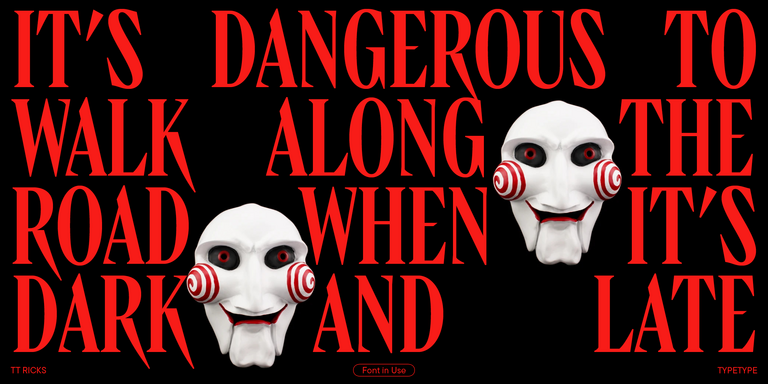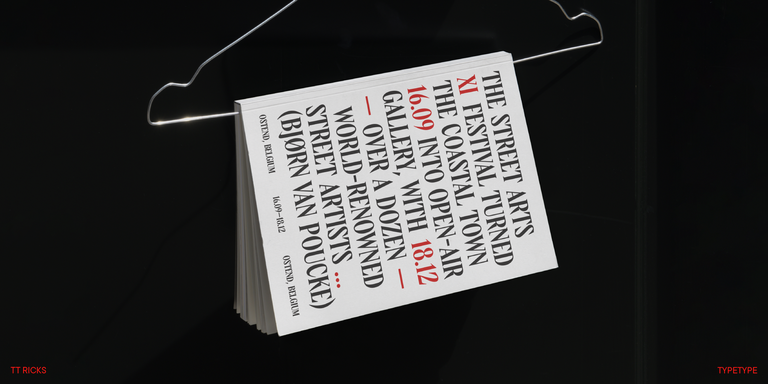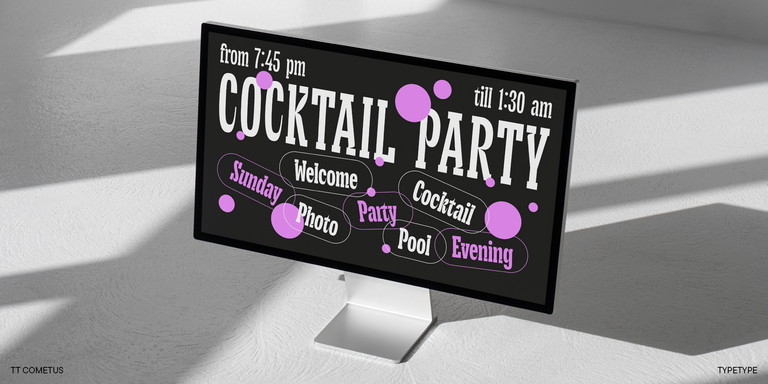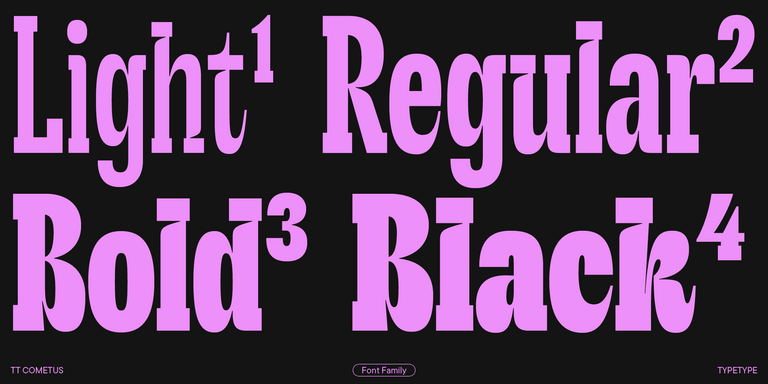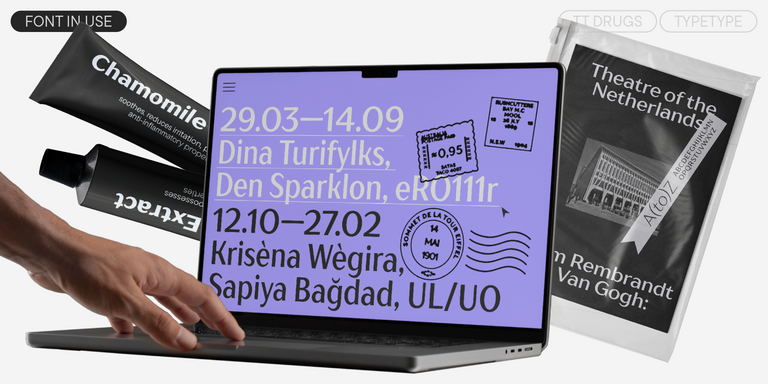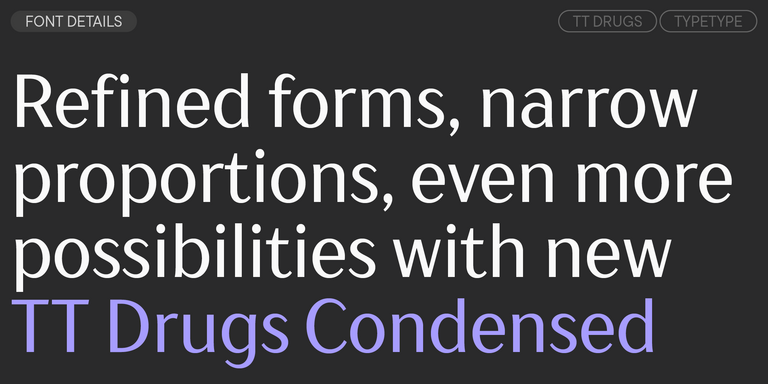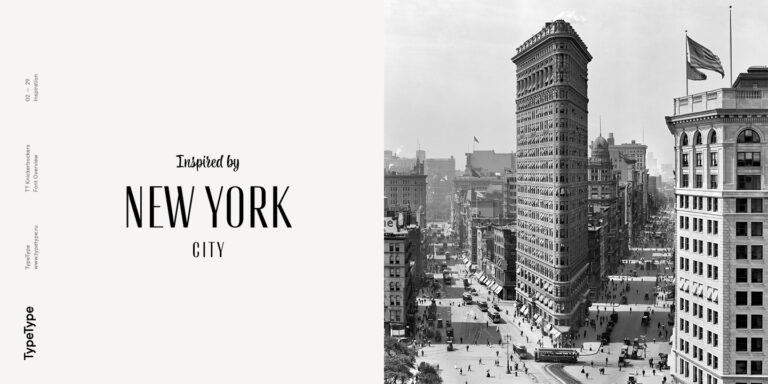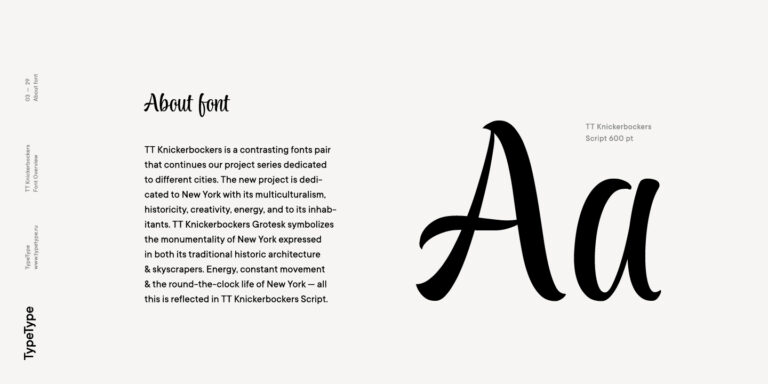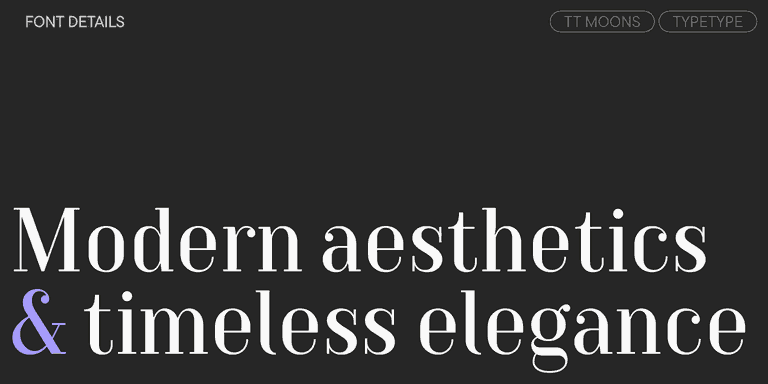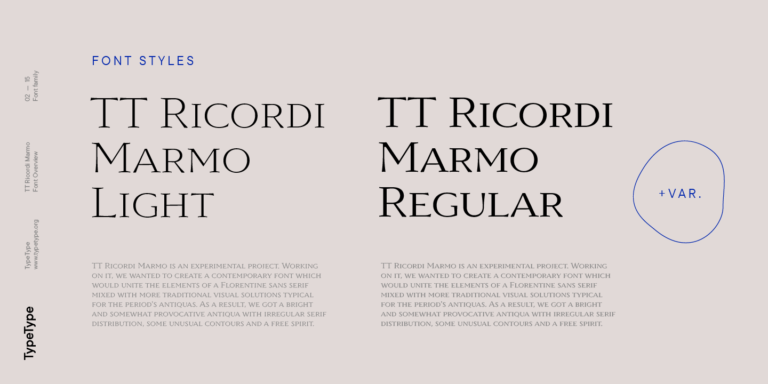
TT Moons est une serif fine et contrastée. Cette famille de caractères fonctionne particulièrement bien dans les designs classiques. TT Moons appartient au style des typographies modernes glyptales.
Polices similaires à Nimbus Roman No. 9 L
Si vous en avez assez des polices surutilisées et que vous recherchez des polices similaires à Nimbus Roman No. 9 L, découvrez nos meilleures alternatives à Nimbus Roman No. 9 L gratuites à essayer, qui présentent des caractéristiques proches ainsi que des éléments de design nouveaux et uniques. Certaines polices appartiennent à la même catégorie typographique, tandis que d’autres conviennent aux mêmes usages ou partagent des traits similaires, tout en se distinguant par leurs détails ou leurs proportions spécifiques.
Chez TypeType, vous trouverez des polices innovantes comme Nimbus Roman No. 9 L, et même mieux : voici une sélection d’alternatives à Nimbus Roman No. 9 L remarquables et moins répandues. Utilisez cette liste de polices de haute qualité similaires à Nimbus Roman No. 9 L selon vos besoins. Notre sélection offre un éventail plus large d’options pour choisir la meilleure police pour votre projet et renouveler vos designs. Toutes les polices présentées dans cette collection sont disponibles dans plusieurs formats et à des prix accessibles, afin de répondre à tous vos besoins !
Trouvez une excellente police de remplacement pour Nimbus Roman No. 9 L et essayez de recréer une ambiance similaire ainsi que l’émotion souhaitée en l’utilisant dans vos designs. Chaque police présentée sur cette page est une alternative à Nimbus Roman No. 9 L, avec une apparence très proche.
TT Drugs est une typographie sans empattements qui se distingue par son contraste élevé.
TT Cometus est une typographie expressive qui captive dès le premier regard.
TT Ricks est une serif flamboyante de style elzévirien pour laquelle des mots comme « mignonne » ou « calme » ne conviennent absolument pas.
TT Ricordi Marmo est un projet expérimental original inspiré des inscriptions de la basilique Santa Croce à Florence.
TT Knickerbockers Grotesk est une sans serif étroite et contrastée dont les éléments caractéristiques nous replongent dans le New York du XIXe siècle.